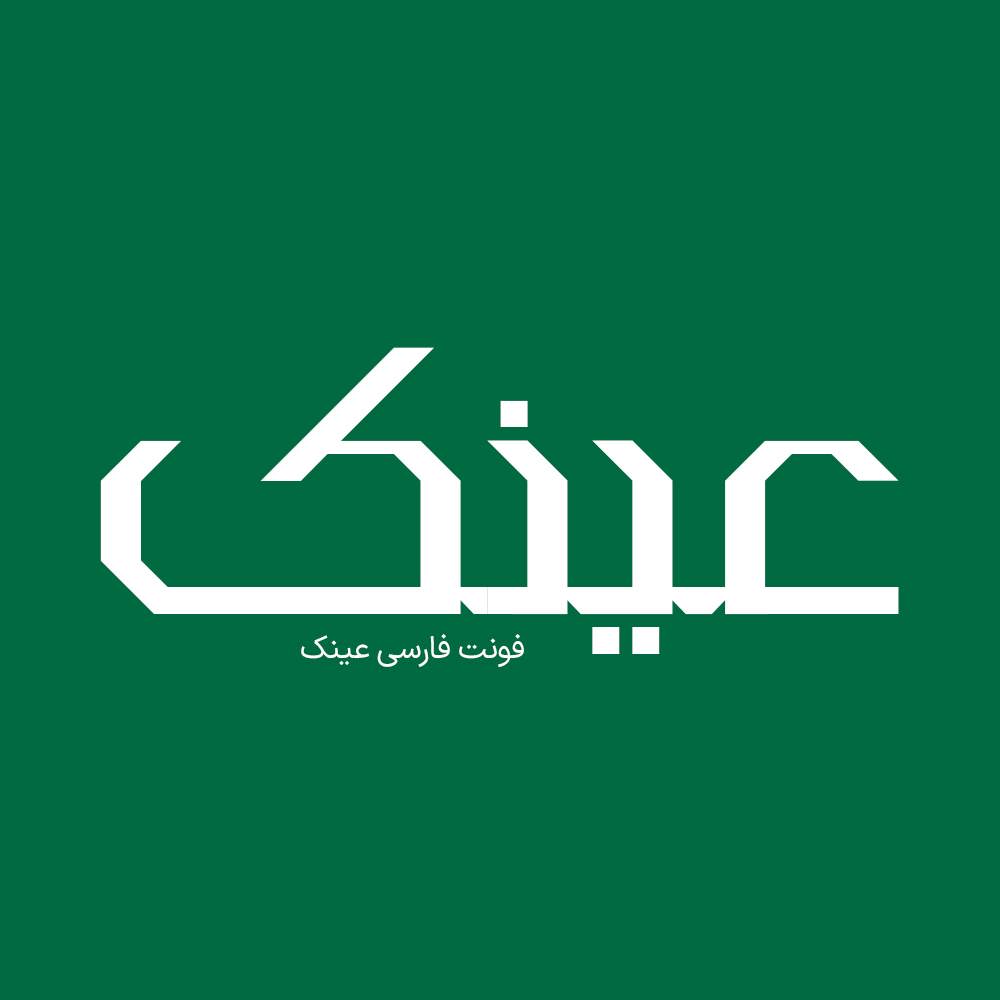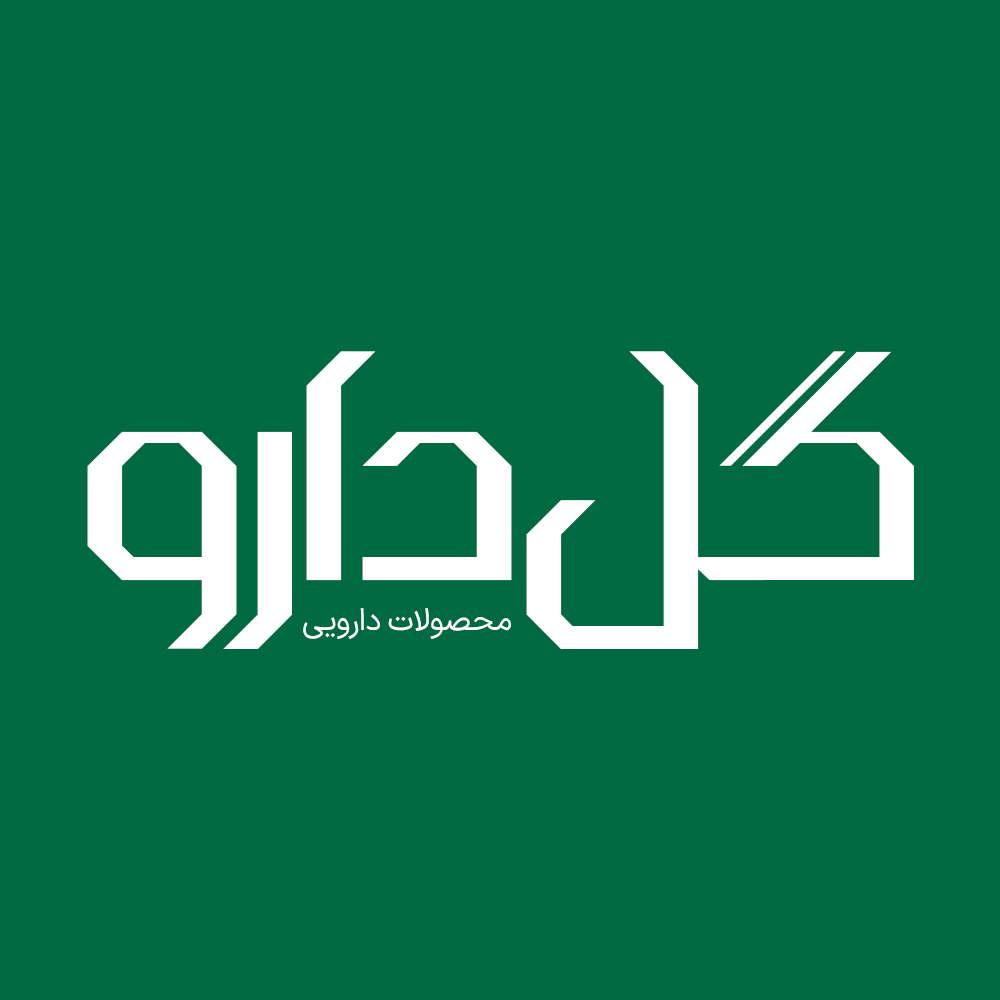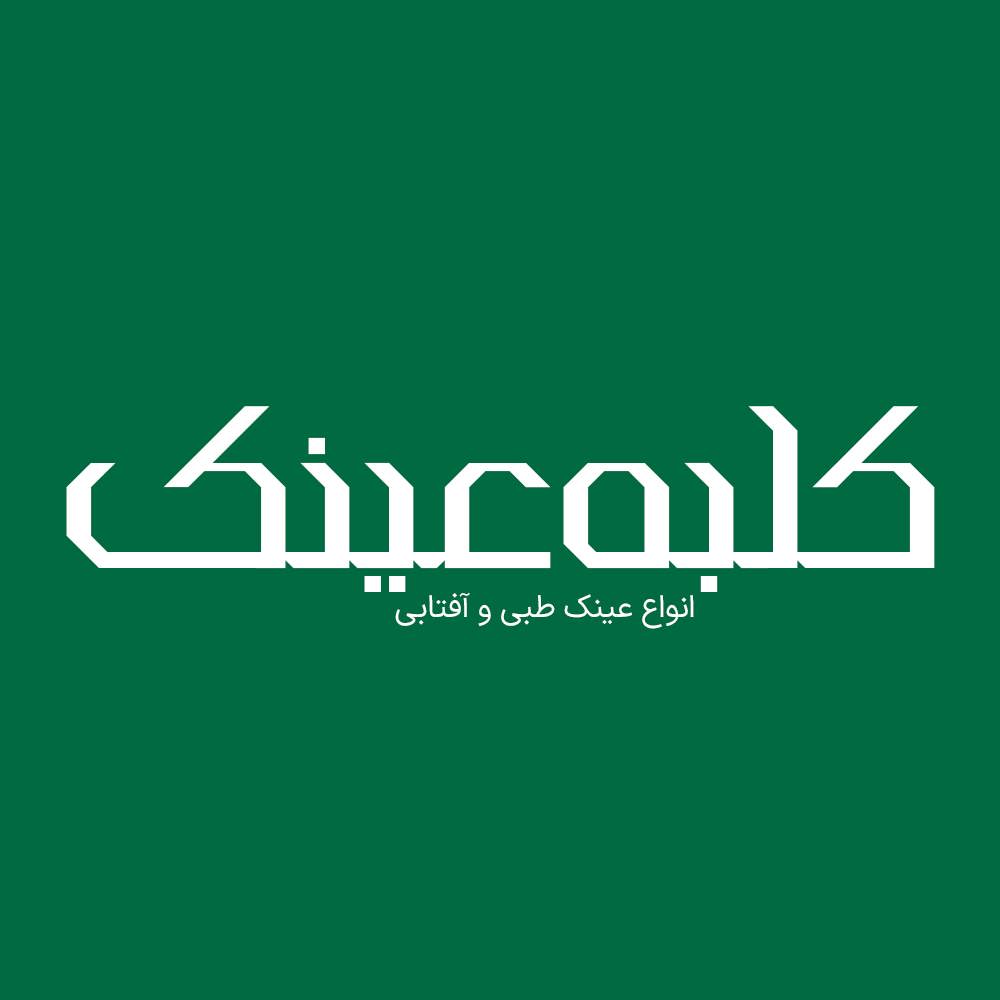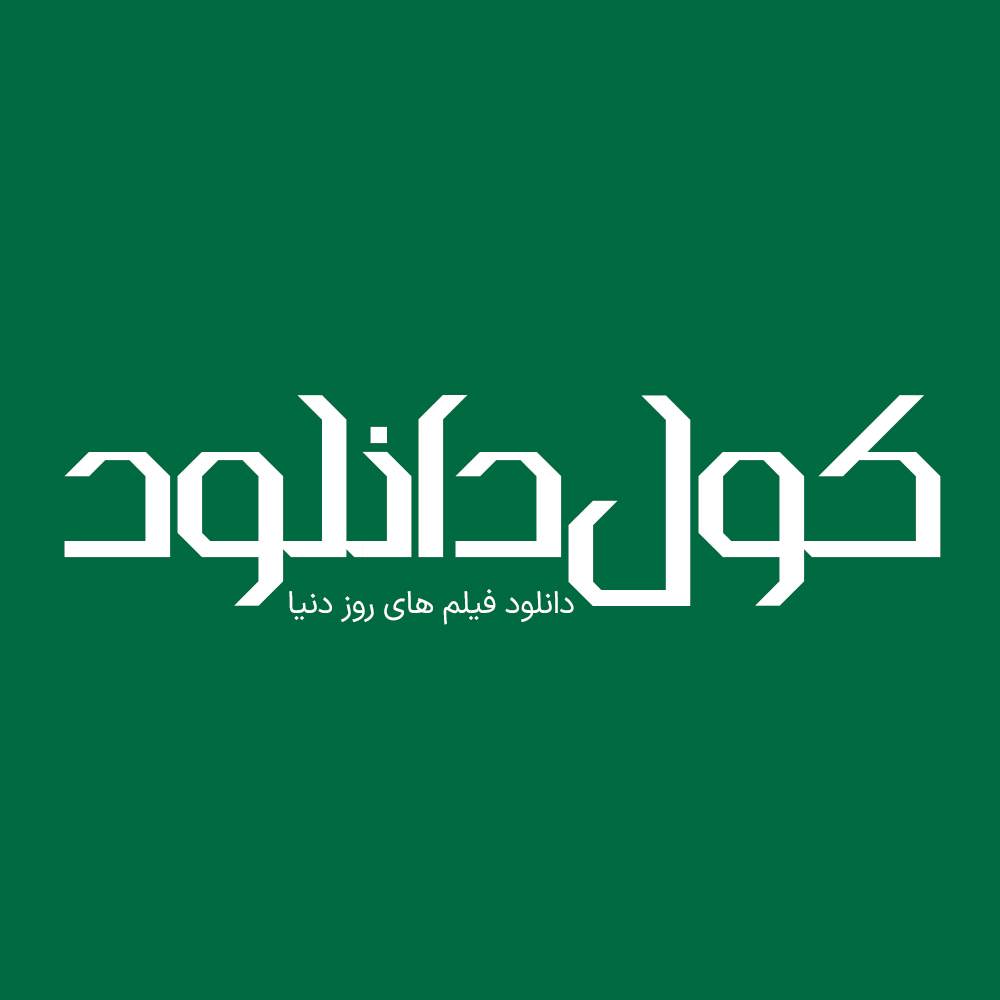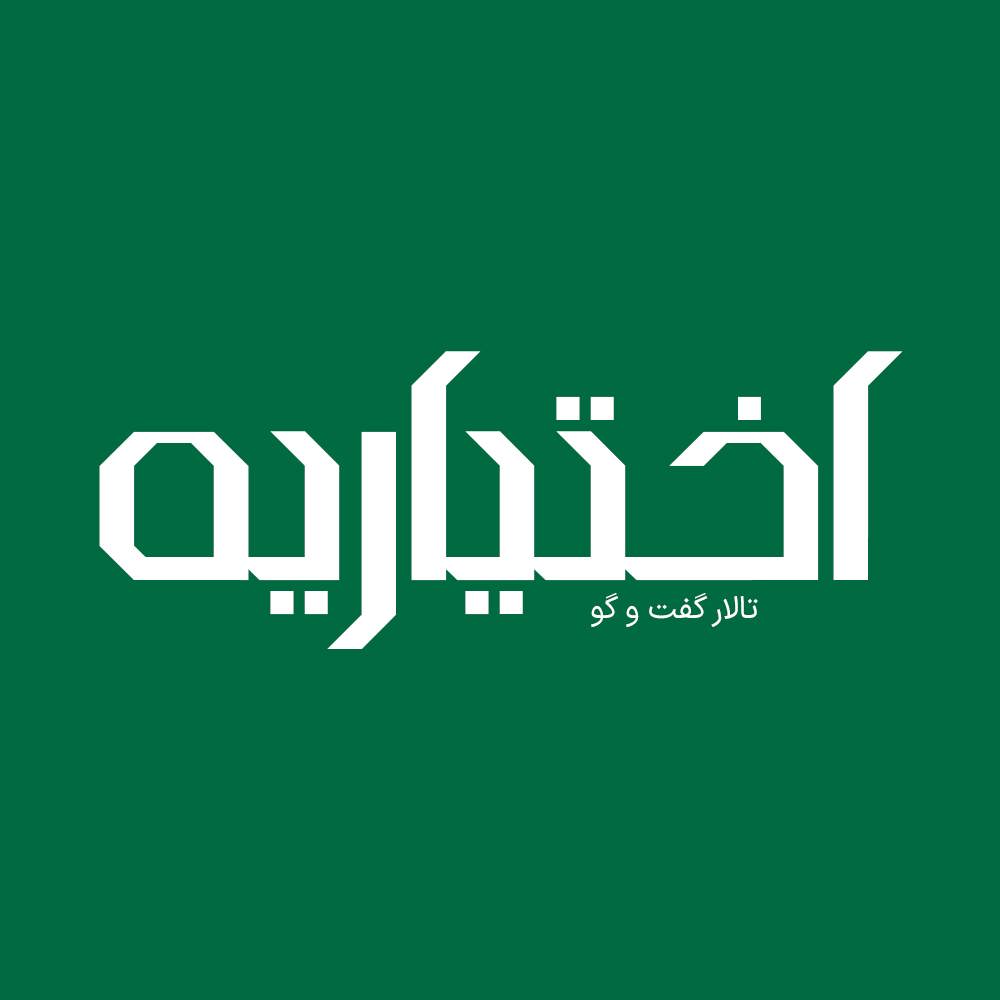
فونت فارسی عینک Eynak Font
فونت فارسی عینک تایپ فیسی که تلاشی وافر در جهت انسجام در کلمات به کمک تنظیم دقیق فاصلهی حروف بوده انجام گردیده است. فونت لوگو عینک قلمی معتدل، منظم و واضح است که انتخابی بسیار مناسب در متون ادبی و مطبوعاتی، عنوان، طراحی لوگوتایپ، طراحی تایپوگرافی و… می باشد.
خوانایی بالای فونت لوگوتایپ عینک به سبب رعایت جزئیات و زوایای داخلی و خارجی سطوح فونت لوگو فارسی در نوع خود بی نظیر می باشد. پس می توانید از فونت عینک در جهت خلق متن های های زیبا و جذاب استفاده نمائید.
فونت عینک یک فونت تک وزن بولد با کاربرد طراحی لوگوتایپ و طراحی های مختلف همچون کتاب و تولید محتوای متن های کوتاه و عناوین می باشد. این فونت با فرمهای سخت و نرم خود مناسب استفاده در لوگوهای نوشتاری می باشد. همچنین از این فونت در طراحی تابلوهای چلنیوم هم به دلیل ساختار منحصر به فردش می توانید استفاده کنید. در ادامه برای شما نمونه تایپ های این محصول حرفه ای رو آماده کردیم که میتونید مشاهده کنید.
پیشنمایش و نمونه تایپ های فونت عینک